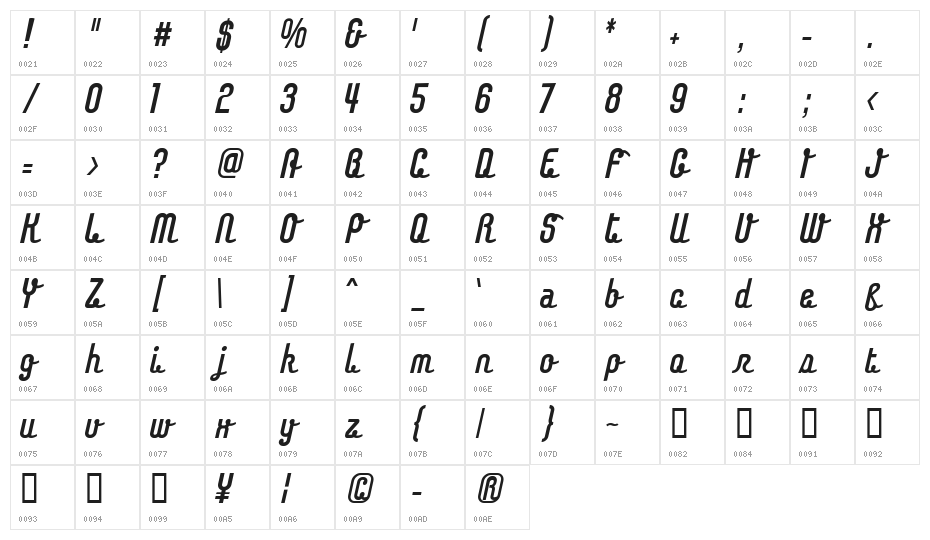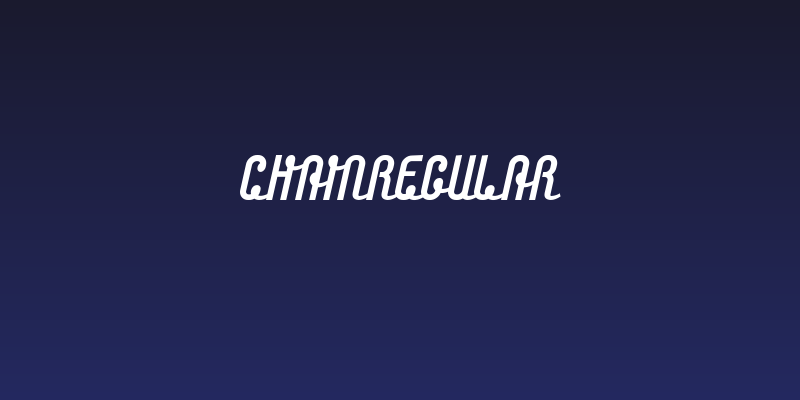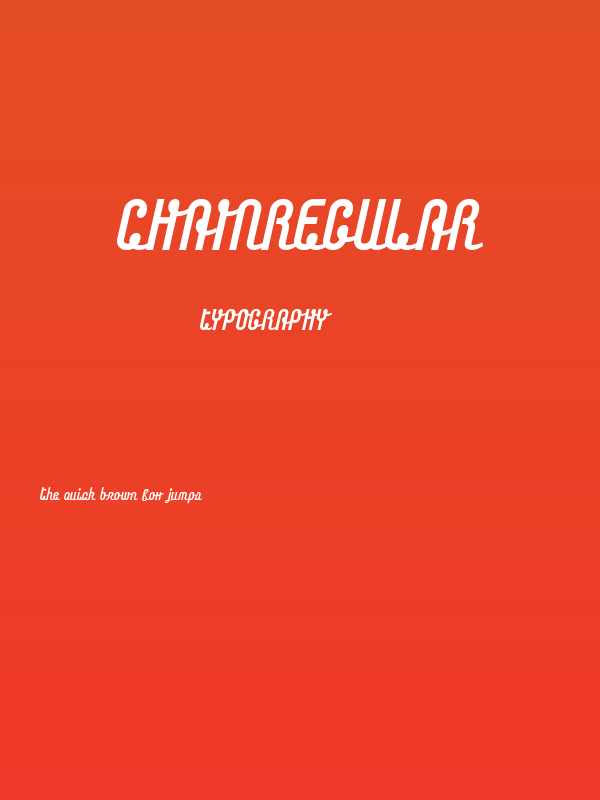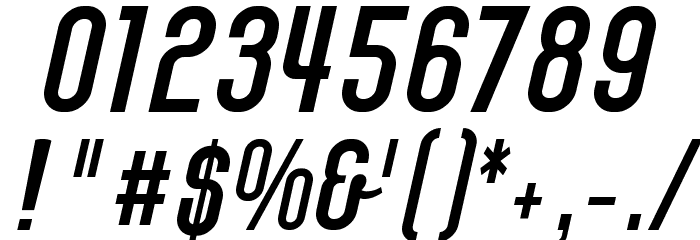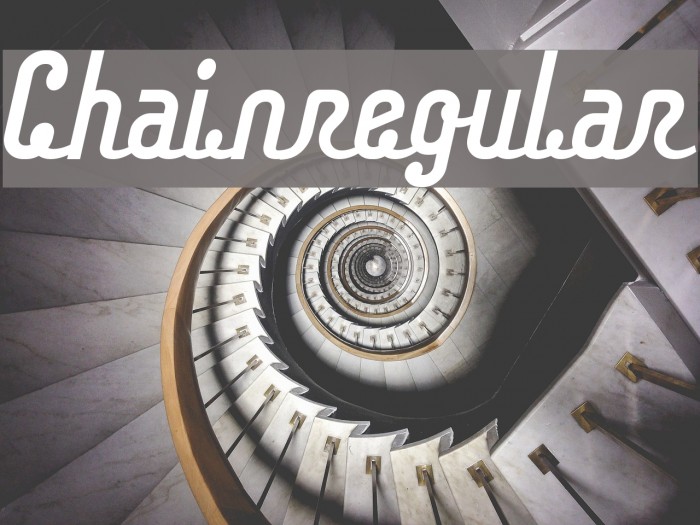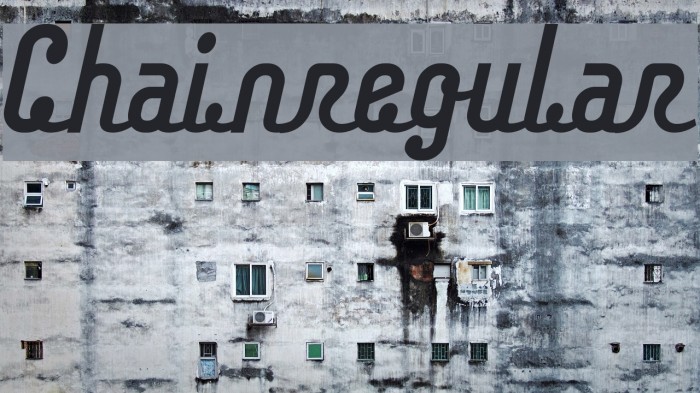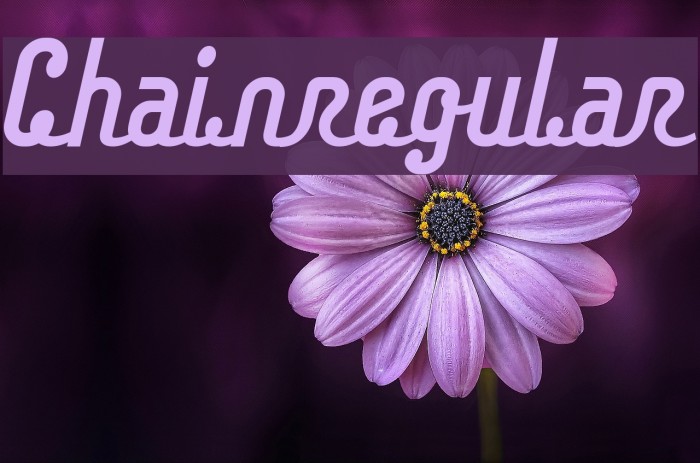
Chainregular Font
| Caso de uso | Headlines, Logos, Branding |
| Proyectos propuestos | Ideal for branding, logo design, packaging, and editorial headlines where a modern and dynamic look is desired. |